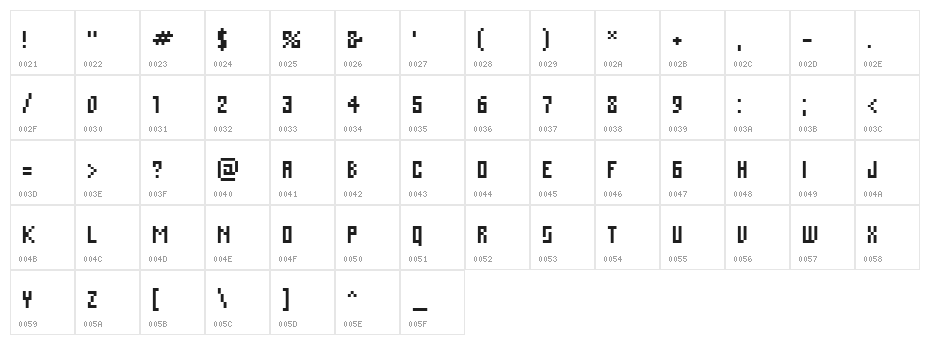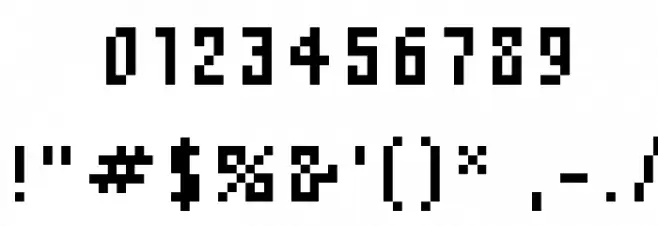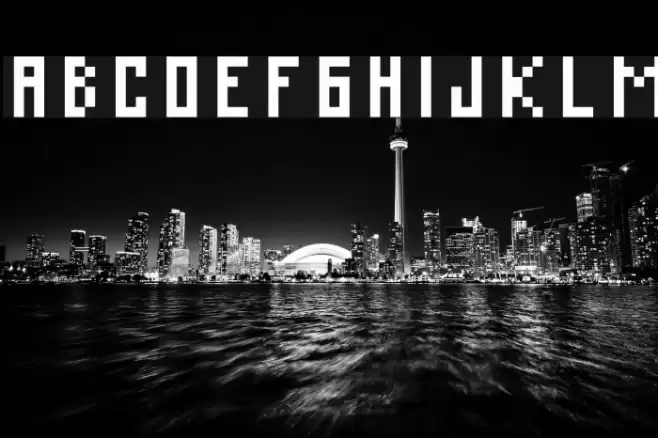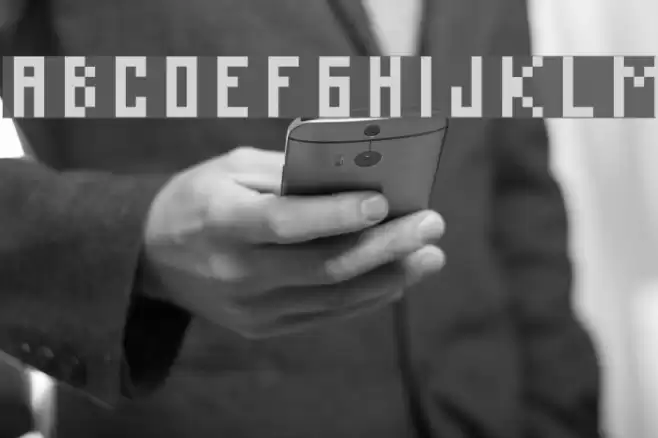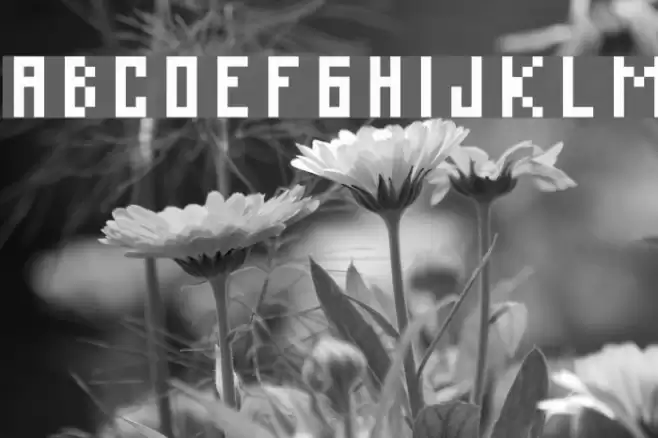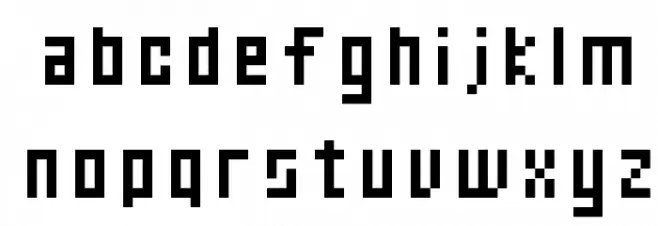
C Web Large Font
✎ Pixel
| Kategorien | Pixel |
| Gesamtstil | Vintage |
| Anwendungsfall | Logos, Headlines, Digital Art |
| Vorgeschlagene Projekte | Ideal for retro video game designs, digital art projects, tech-themed posters, and nostalgic branding. |